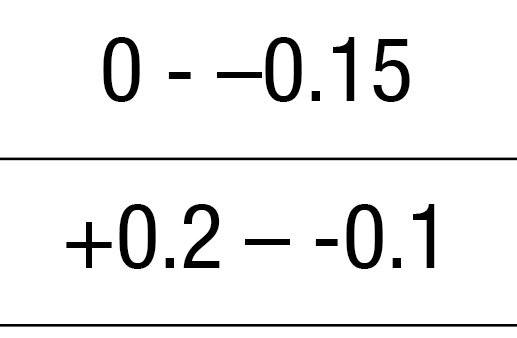
[Mitglied d2d7…] Geschrieben Juli 8, 2014 Teilen Geschrieben Juli 8, 2014 Hallo zusammen, ich sitze derzeit an einem Katalog, der viele technische Daten beinhaltet. Bisher wurde der Katalog im Ausland erstellt und für "von bis" die Tilde benutzt. Bei technischen Daten natürlich ungünstig, da man es bei uns als circa/ungefähr deutet. Nun stellt sich mir gerade die Frage, wie ich "von bis minus" korrekt darstelle. Kann mir dabei evtl. jemand helfen? Das wäre super! Vielen Dank! Link zu diesem Kommentar
[Mitglied 508e…] Geschrieben Juli 8, 2014 Teilen Geschrieben Juli 8, 2014 Müsste das nicht eh andersherum – die negativen Zahlen links und die positiven (größeren) rechts? (Das Problem bleibt dann natürlich trotzdem bei zwei negativen Zahlen) Link zu diesem Kommentar
Ralf Herrmann Geschrieben Juli 8, 2014 Teilen Geschrieben Juli 8, 2014 Nun stellt sich mir gerade die Frage, wie ich "von bis minus" korrekt darstelle. Wenn du die Freiheit hast: genau so! Also mit dem Wort »bis«. Link zu diesem Kommentar
[Mitglied 109…] Geschrieben Juli 8, 2014 Teilen Geschrieben Juli 8, 2014 Im Fließtext verwenden wir »bis«, in Grafiken, Tabellen »–«, auch um Grafiken, Tabellen etc. übersetzungsneutral zu halten. Link zu diesem Kommentar
[Mitglied d2d7…] Geschrieben Juli 8, 2014 Teilen Geschrieben Juli 8, 2014 Wenn du die Freiheit hast: genau so! Also mit dem Wort »bis«. Hallo Ralf, leider nicht. Wie gesagt, handelt es sich hierbei um technische Daten, die in Tabellen dargestellt werden. Der Katalog wird auch in mehreren Sprachen erstellt (wie von Bernd angesprochen), daher ist generell eine Zeichensetzung um einiges einfacher. Das Problem kam auch aktuell (nach ca. 600 Seiten) zum ersten mal vor, bisher hatte ich nur "bis" ohne "von", also ohne eine Zahl davor, darzustellen, was ich einfach mit "kleiner als/gleich" ändern konnte. Müsste das nicht eh andersherum – die negativen Zahlen links und die positiven (größeren) rechts? (Das Problem bleibt dann natürlich trotzdem bei zwei negativen Zahlen) Zu Schnitzel: nein, die Daten sind so schon korrekt, es geht speziell bei diesem Beispiel um die Bohrtiefe, daher wird die Negativzahl als zweites gesetzt. Ich bin mir eben nur unsicher, ob kurz oder lang "-" zuerst kommt. Vielen Dank für eure Hilfe! Link zu diesem Kommentar
Ralf Herrmann Geschrieben Juli 8, 2014 Teilen Geschrieben Juli 8, 2014 Im Prinzip muss beides »lang« sein. Minus ist ein eigenes mathematisches Zeichen: http://www.fileformat.info/info/unicode/char/2212/index.htm (Wird aber in der Regel einfach durch den Gedankenstrich dargestellt.) Der Bis-Strich ist wiederum einfach der Halbgeviertstrich/Gedankenstrich. http://www.fileformat.info/info/unicode/char/2013/index.htm Link zu diesem Kommentar
[Mitglied 9fb8…] Geschrieben Juli 8, 2014 Teilen Geschrieben Juli 8, 2014 In einer Tabelle würde ich das in zwei Spalten mit "min." und "max." lösen. Link zu diesem Kommentar
[Mitglied catf…] Geschrieben Juli 8, 2014 Teilen Geschrieben Juli 8, 2014 Und wie wäre es mit +0,3 ... ‒0,6 ? Link zu diesem Kommentar
[Mitglied 9fb8…] Geschrieben Juli 8, 2014 Teilen Geschrieben Juli 8, 2014 Da wäre das Minus eigentlich auch falsch Eine Ellipse als Bis-Strich in technischen Tabellen hab ich noch nie gesehen. Ist das international bekannt? Link zu diesem Kommentar
[Mitglied Wrzl…] Geschrieben Juli 8, 2014 Teilen Geschrieben Juli 8, 2014 Bisher wurde der Katalog im Ausland erstellt und für "von bis" die Tilde benutzt. Bei technischen Daten natürlich ungünstig, da man es bei uns als circa/ungefähr deutet. Für ungefähr die Tilde zu nutzen ist auch hierzulande m. E. eine schlechte Lösung und vermutlich ursprünglich als Notbehelf entstanden, wenn man kein ≈ zur Hand hat. ~ ist eigentlich für mathematische Äquivalenz reserviert (z. B. geometrische Ähnlichkeit). Vielleicht ist das Beibehalten der Tilde gar keine so schlechte Idee, wenn es möglich ist, diese Notation einmal einzuführen, also z. B. in der Tabellenunterschrift zu schreiben: »~ steht hier für bis.« Die einzigen sauberen Alternativen zu »+0,2 – −0,5«, die mir einfallen, wären so etwas wie »0,2 ≥ x ≥ —0,5« oder »x ∈ [−0,5;0,2] – aber das ist vermutlich ebenfalls nicht schön zu lesen und Deiner Leserschaft zu mathematisch. Link zu diesem Kommentar
[Mitglied Chri…] Geschrieben Juli 8, 2014 Teilen Geschrieben Juli 8, 2014 +10, … , −5 E: Ach, hatte catfonts schon geschrieben, seh ich gerade. Link zu diesem Kommentar
[Mitglied 109…] Geschrieben Juli 8, 2014 Teilen Geschrieben Juli 8, 2014 In einer Tabelle würde ich das in zwei Spalten mit "min." und "max." lösen. Diese Variante verwenden wir auch. MIN und MAX kann man in Katalogen für fachkundige Techniker auch in vielen Sprachen so stehen lassen. Link zu diesem Kommentar
[Mitglied pixe…] Geschrieben Juli 8, 2014 Teilen Geschrieben Juli 8, 2014 Wie wäre es mit einem Pfeil? +0.2 → −0.1 +0.2 ↔ −0.1 Link zu diesem Kommentar
[Mitglied Tobi…] Geschrieben Juli 8, 2014 Teilen Geschrieben Juli 8, 2014 Der Pfeil heißt „geht gegen“ und dass aus der 0,2 irgendwann mal ne -0.1 wird ist unwahrscheinlich Die Ellipse kenne z.B. aus Listen wie n = 1, 2, 3, …, i. Ich würde sie auch für „bis“ verstehen, das ist aber glaube ich nicht die Norm/Konvention. Link zu diesem Kommentar
[Mitglied catf…] Geschrieben Juli 8, 2014 Teilen Geschrieben Juli 8, 2014 Das ich jetzt zum falschen strich fürs Minus gegriffen hab, tut mir leid, ich hab es in der Windoofd-Zeichentabelle schlicht nicht gefunden, da Windoof7 die Zeichentabelle nicht nach Unicode sortiert hat, sondern irgenfwie (un)logisch - da sind dann zwar die Mathe-Sysmbole zusammengefasst, aber Minus ist nicht dabei, wohl aber kurz darpber die verschiedenen anderen Binde-, Gedanken-, m-, n, und Halb, und Geviertstriche. Mir ging es ja einzig um die Ellipse, die dann dieses unschöne aufeinandertreffen verschidener Striche, die dann noch in der Höhe herumputseln. Ich habe in verschiedenen Schriftarten auf dem Codeplatz für "minus" auch schon alles mögliche gesehen: ein Strich von gleicher Länge und in gleicher Höhe wie der waagerechte Strich des + (idealerweise sollte es so sein), aber auch: einfach den normalen Devis, einen Halbgeviertstrich aber eben auf andere Höhe wie im +, ein Minus das in der Höhe an der Unterkante des + hängt, ein Strichg, der in keine Kategorie passt... Link zu diesem Kommentar
[Mitglied Chri…] Geschrieben Juli 8, 2014 Teilen Geschrieben Juli 8, 2014 Die Ellipse kenne z.B. aus Listen wie n = 1, 2, 3, …, i. Ich würde sie auch für „bis“ verstehen, das ist aber glaube ich nicht die Norm/Konvention. Genau, aber selbst wenn nur zwei Zahlen A und B neben der Ellipse stehen, liest man meiner Meinung nach: A, B und alles dazwischen. Link zu diesem Kommentar
[Mitglied CRud…] Geschrieben Juli 17, 2014 Teilen Geschrieben Juli 17, 2014 Nö, im Kontext hätte ich jetzt schon gedacht daß man dies versteht. Im entsprechenden Umfeld würde man dies problemlos z.B. als Toleranzbereich erkennen. Die Leute die sich einen solchen Katalog ansehen werden ja vermutlich eine ähnliche Angabe erwarten. Finde ich jetzt spontan besser als irgendein Bandwurm-Strichelchen-Konstrukt, welches dann zwar typografisch korrekt ist, welches man aber ziemlich dämlich aussieht und welches dann auch nicht verständlicher ist. Link zu diesem Kommentar